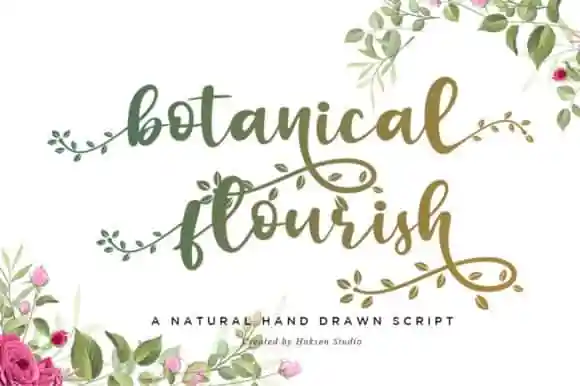
Botanical Flourish Calligraphy Font – Fonte Grátis
Botanical Flourish Calligraphy Font
A Botanical Flourish Calligraphy Font é uma escolha perfeita para quem busca uma mistura suave entre antiguidade e contemporaneidade. Seu estilo elegante e fluido evoca um toque de casualidade, tornando-o uma opção versátil que se adapta a diversos usos. Este font, desenvolvido por Haksen na 99designs, foi criado para atender aos mais exigentes designers gráficos. Suas linhas leves e fluidas trazem um toque de elegância à cada letra, enquanto os alternativos meticulosamente cuidados dão a ele um aspecto que é tanto de época quanto atual. A variedade da linha base e o acesso fácil aos caracteres e desenhos alternativos permitem uma liberdade inigualável no design, tornando-a perfeita para criações que valorizam tanto o equilíbrio como a originalidade visual. Com seu estilo botânico atemporal, esta font é um ótimo complemento ao seu trabalho de design.